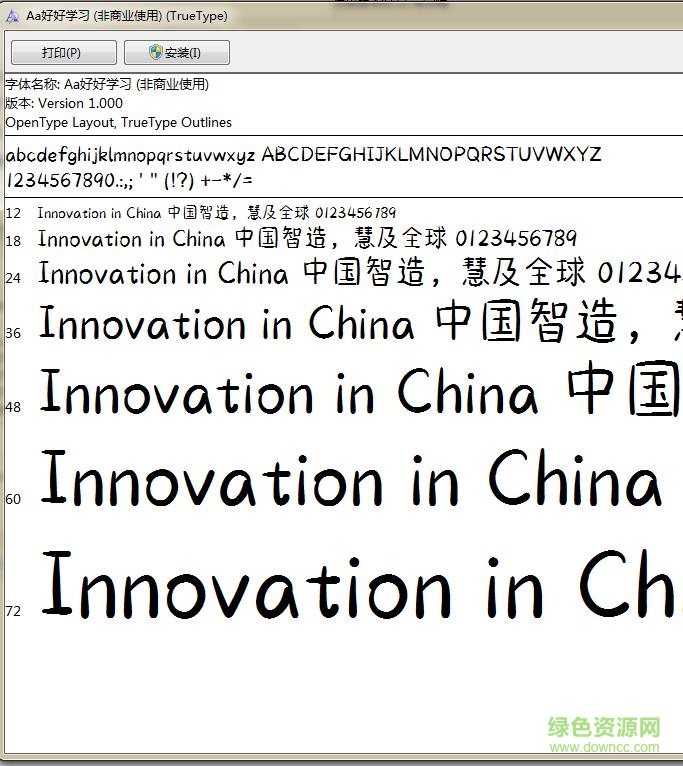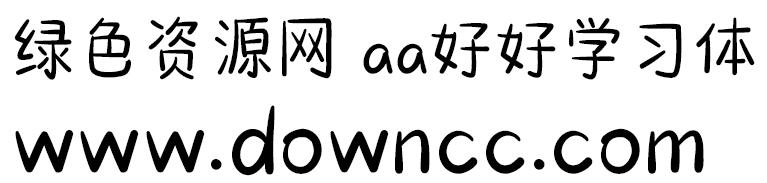
aa好好學習體ttf能夠讓你在學習的時候使用這款字體獲得無窮的學習動力,這款字體十分有趣,字體樣式精美無比,通過這款字體,讓你能夠感受到充沛的學習體驗,快來綠色資源網(wǎng)下載吧!
我要學習,學習使我超級快樂。學習伴我成長,只有通過學習我們才能夠進步,為了能夠更上一層樓,請用我這款字體進行學習吧!